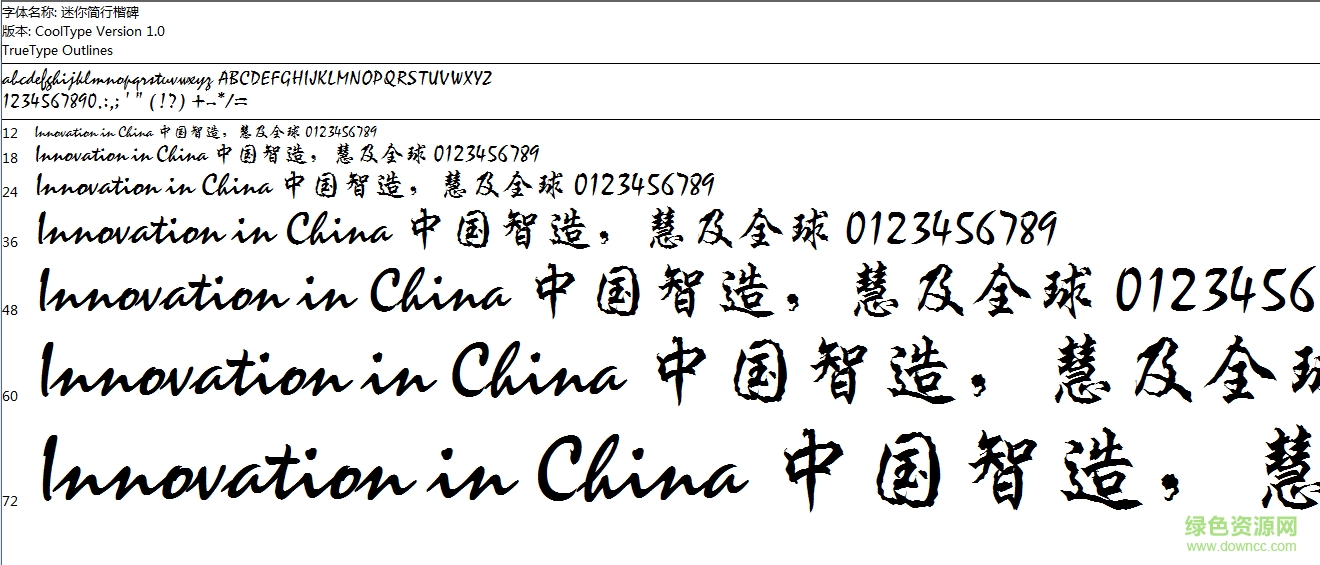
迷你簡行楷碑是一款非常漂亮的簡體行楷字體,這款字體飄逸大方得體,整體效果十分出眾,深受書法愛好者的青睞,并且這款字體使用范圍非常的廣泛,有需要的朋友歡迎來綠色資源網(wǎng)下載體驗!
迷你簡行楷碑字體這個字體是行楷中的一種,但是還是有點區(qū)別的,非常適合廣告設(shè)計、平面設(shè)計、印刷包裝、正文標題等人員使用。